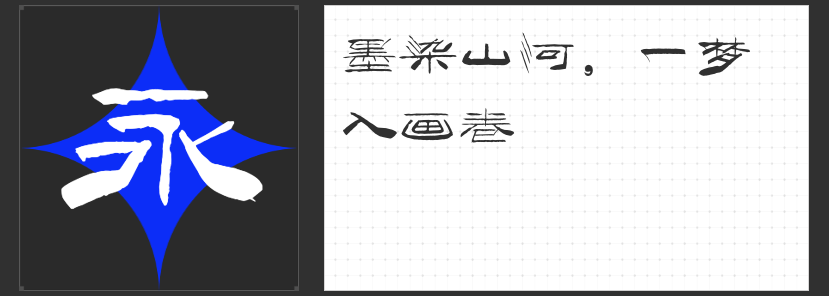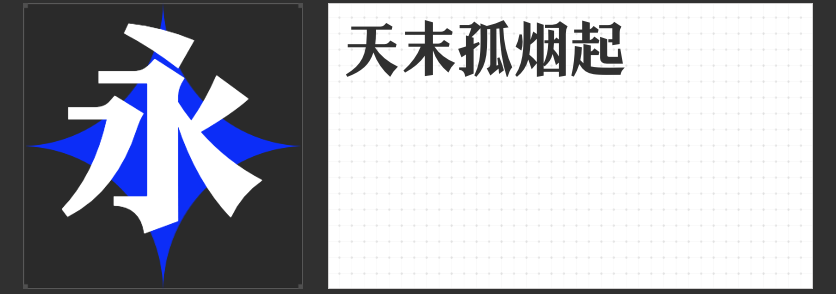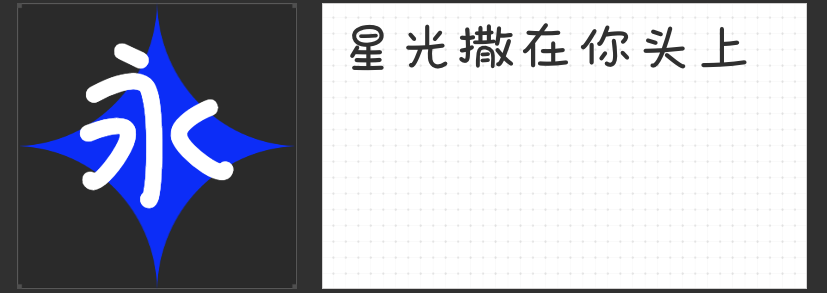
封面设计新秀:四款创意字体推荐
在封面设计中,字体选择至关重要,它不仅影响着整体的视觉效果,还能传达出特定的情感和氛围。今天,就为大家推荐四款适合用于封面设计的创意字体。
1.云书法铁笔隶书体
这款字体融合了传统隶书与现代设计元素,笔画粗犷有力,充满金石韵味。其独特的笔触和线条质感,能够赋予封面设计一种古朴而庄重的美感,适合用于历史、文化或传统艺术类的书籍封面。
2.励字雪花特效简
这款字体以其独特的雪花特效而引人注目,轻盈飘逸的雪花元素与简洁明快的字体相结合,营造出一种清新脱俗的氛围。它非常适合用于冬季主题、浪漫小说或儿童读物的封面设计,能够瞬间提升作品的梦幻感和吸引力。
这款字体充满了童趣和野趣,笔画自由奔放,形态各异,仿佛带着孩子们天真无邪的欢笑和探险的足迹。它非常适合用于儿童读物、绘本或教育类书籍的封面设计,能够激发读者的好奇心和阅读兴趣。
4.字圈也字山海明朝
这款字体借鉴了明朝时期的书法风格,笔画流畅而富有韵律感,整体给人一种典雅而庄重的感觉。它适用于历史、哲学、文学等类别的书籍封面设计,能够彰显作品的深度和内涵。
以上四款字体各具特色,无论你是想要打造传统韵味十足的封面,还是追求现代时尚感的视觉效果,都能在其中找到合适的选择。希望这些推荐能够为你的封面设计带来新的灵感和创意!